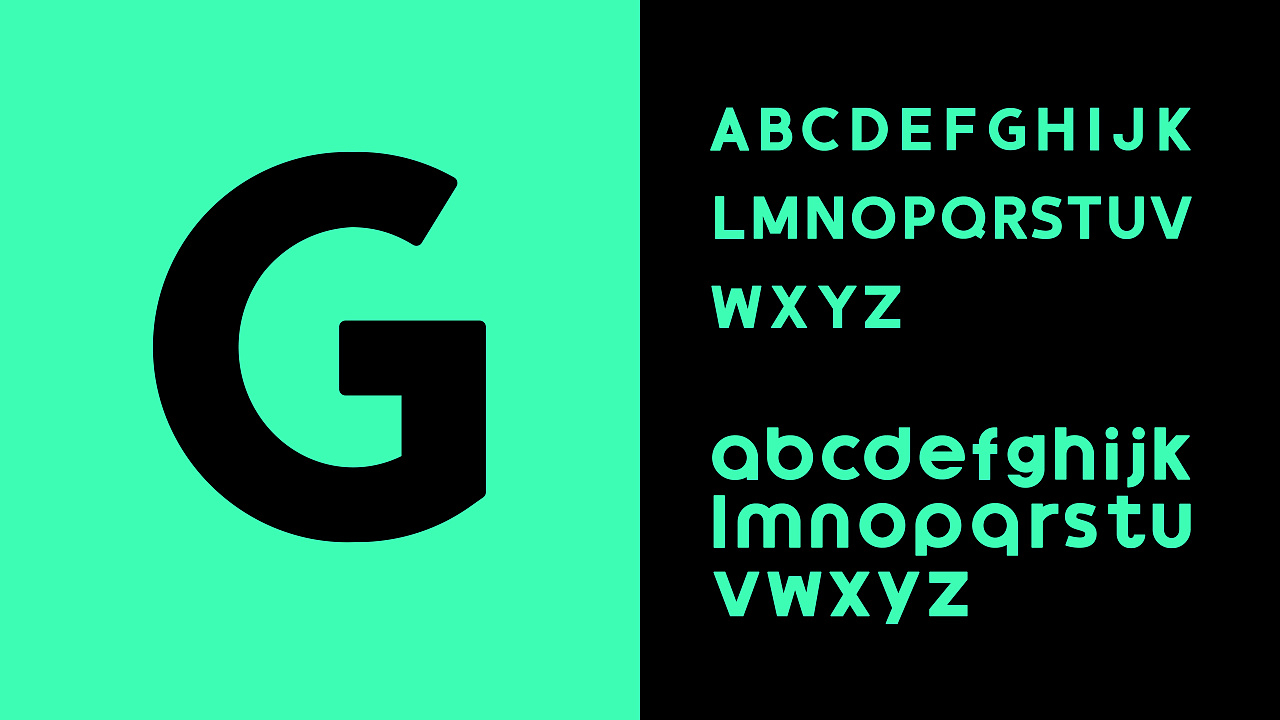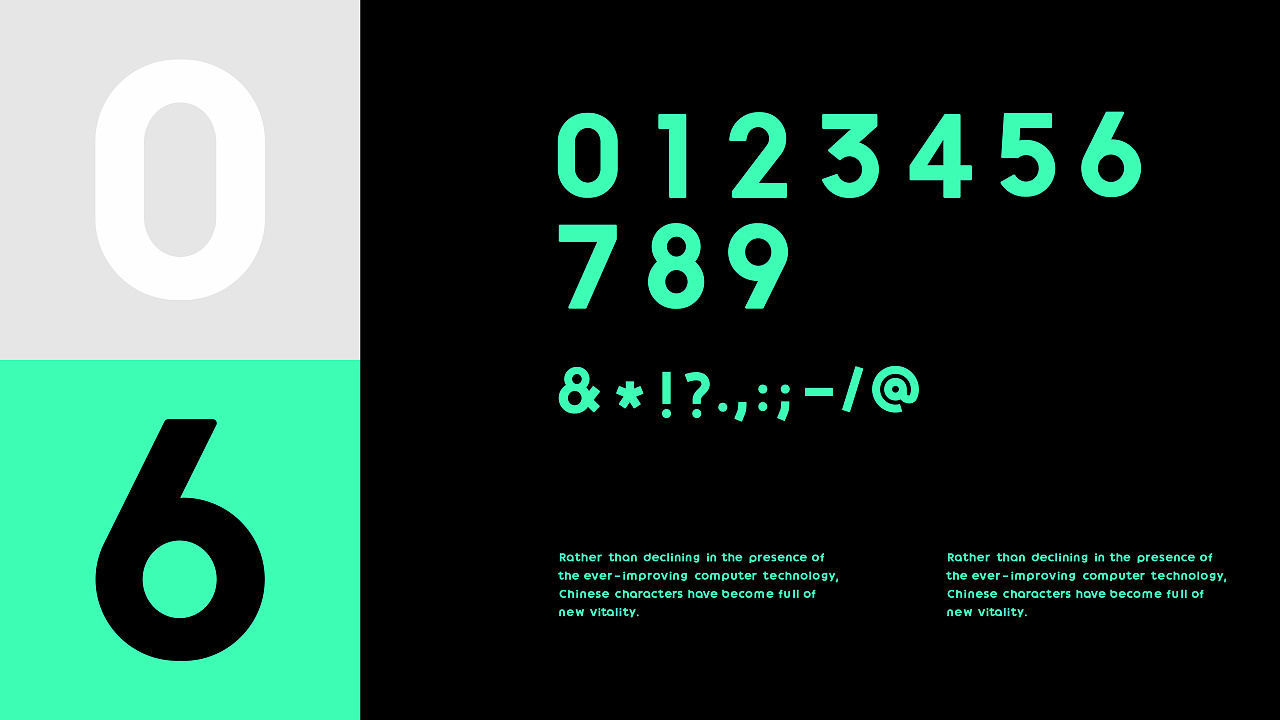
Nice是一款無襯線西文字體,是19年參加方正字體大賽的作品,雖未能獲獎,但個人覺得這款字作為標題來使用是非常不錯的,一直想做成字庫,只怪自己太拖啦,一直到現在才整理出來,免費供各位使用。
生成字庫後小寫有一點小Bug,對齊稍微有點小問題,不過影響不大,大寫比較完整,
作為標題使用是非常不錯的。
字體名稱:Nice Regular和NiceBold